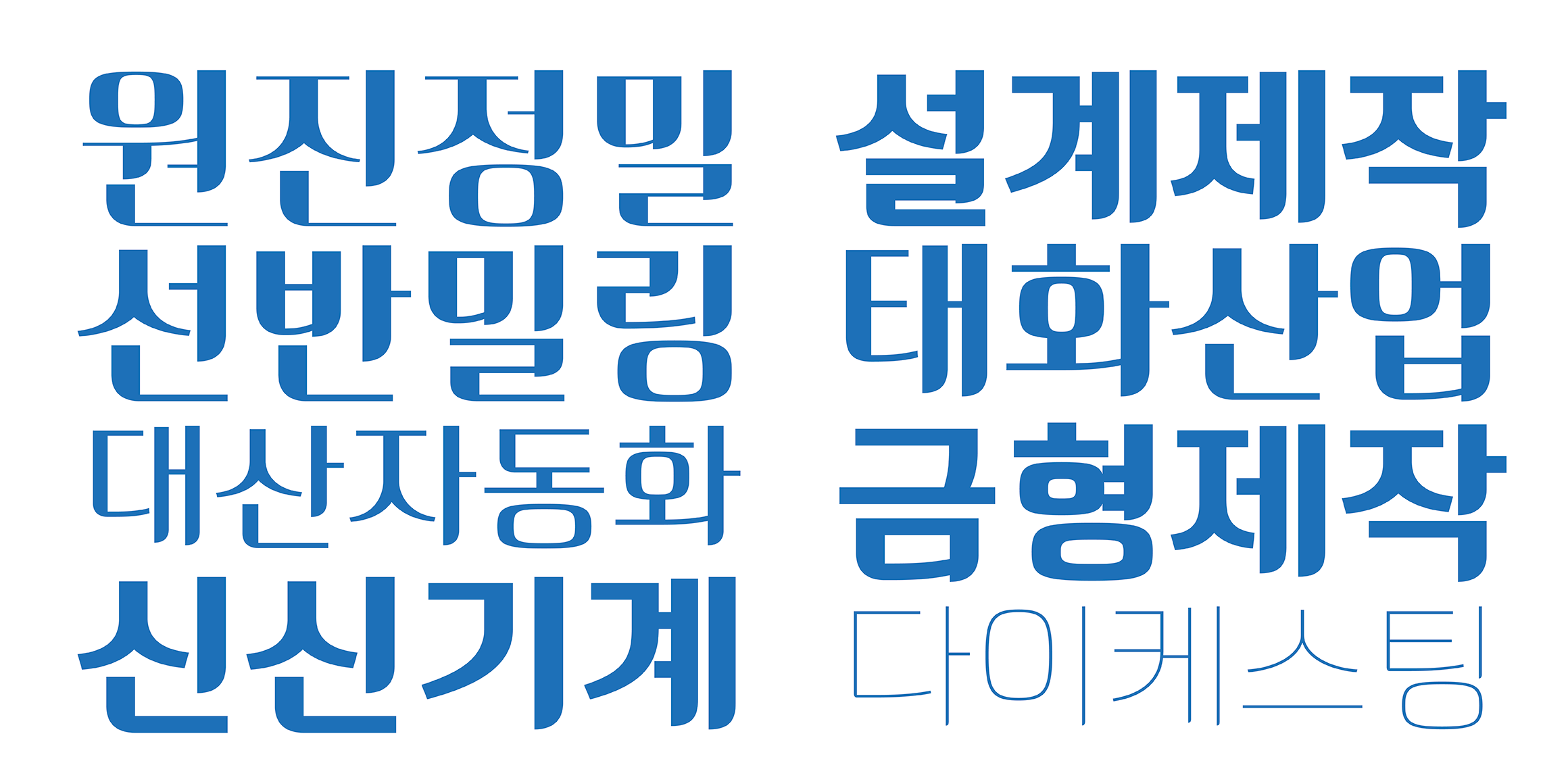
DR셀럽 클래식
셀럽클래식은 산스 기반에 세로기둥 및 세로획의 맺음 부분을 큰 라운드로 표현하여 고전적인 아름다움을 강조하고 있습니다. 모두 6개의 패밀리로 개발되었고 사인이나 패키지디자인에 어울립니다.
• 6종
• 2022
• 이호
• 디스플레이
• DR셀럽 클래식 / DR Celeb Classic